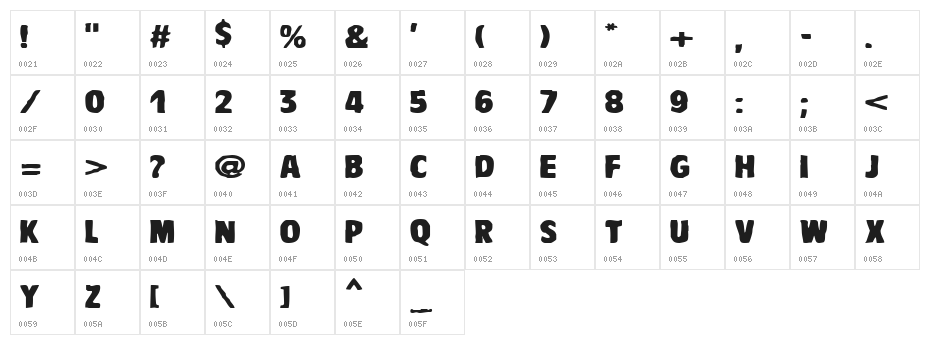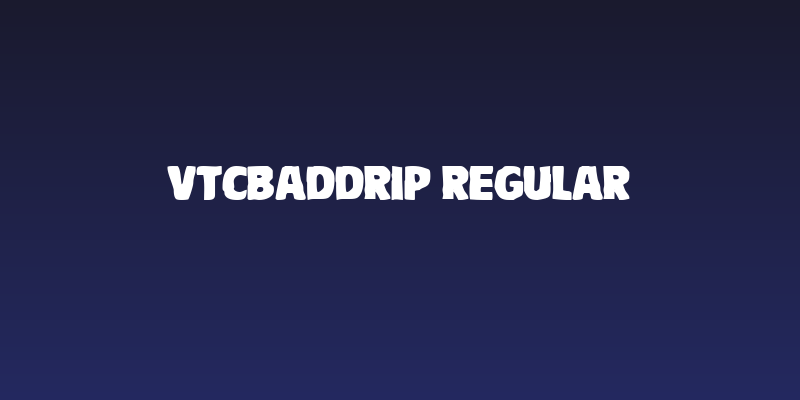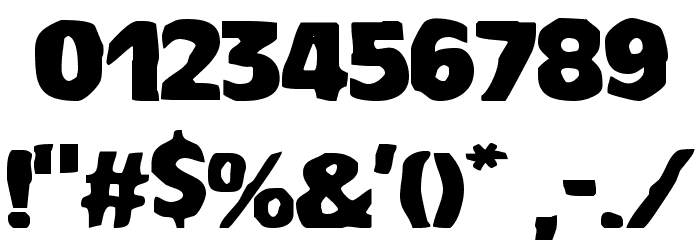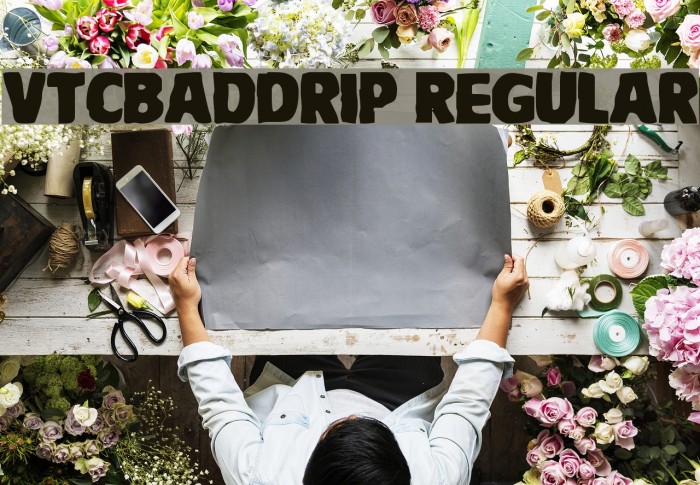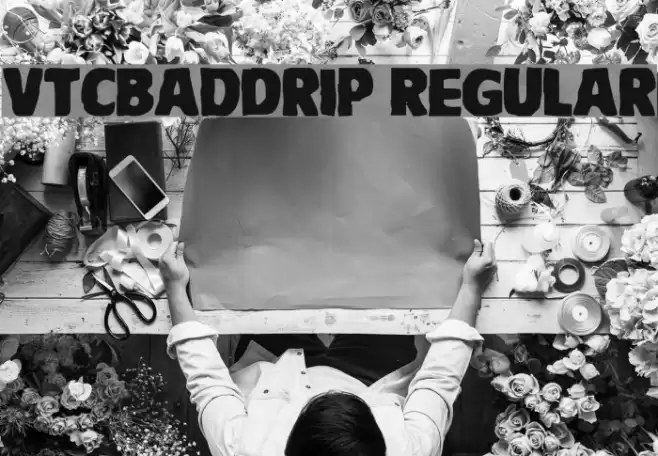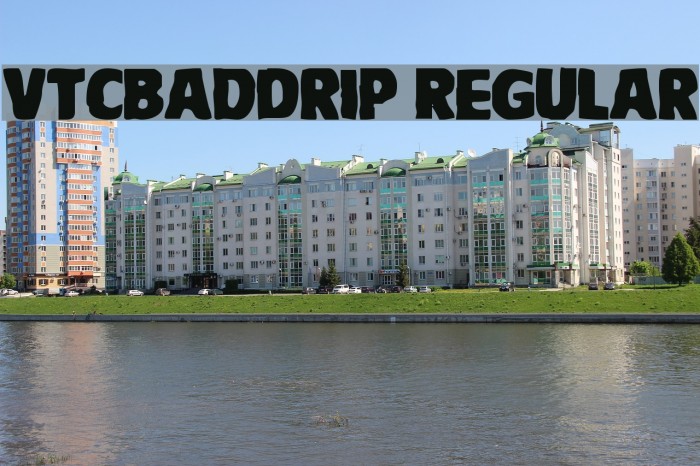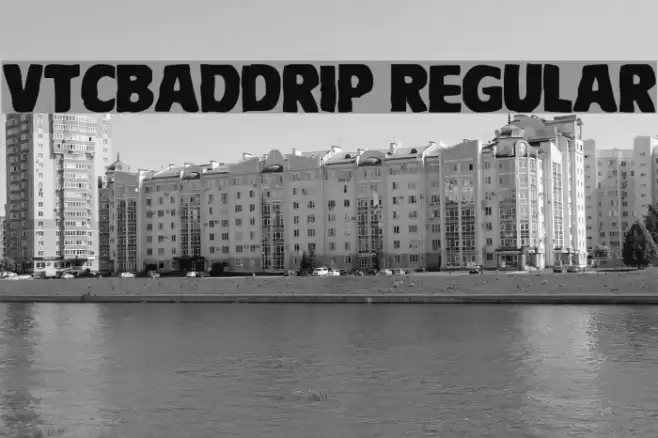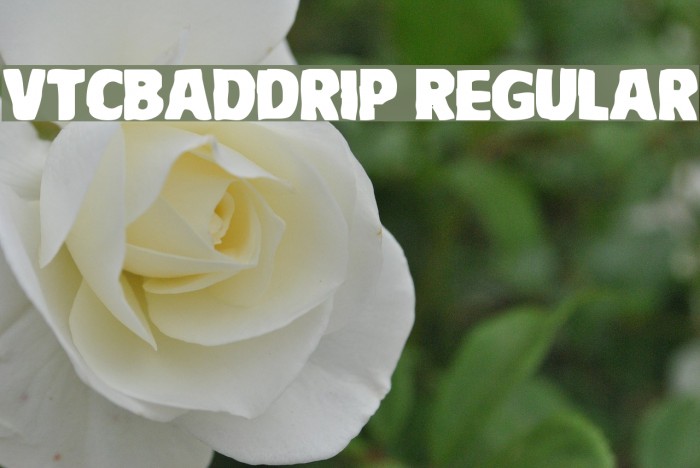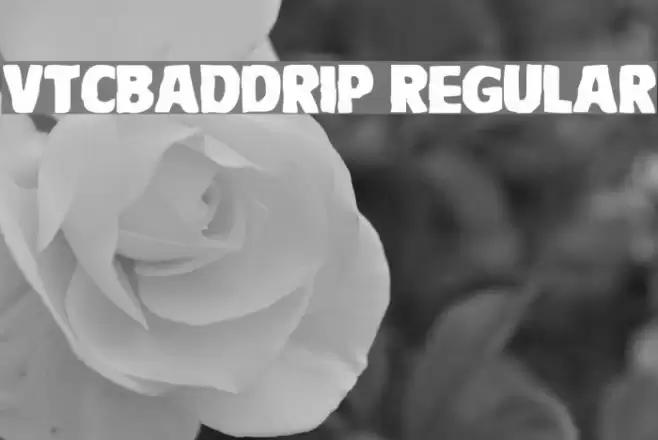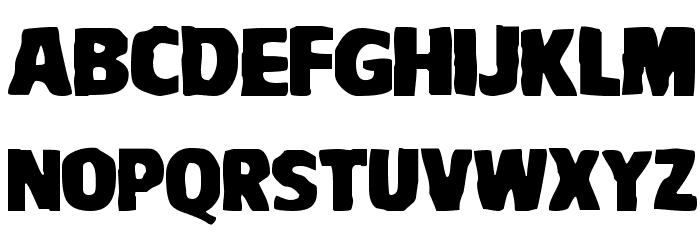
VTCBadDrip Regular Font
| Categorías | Capitals |
| Caso de uso | Headlines, Posters, Logos |
| Proyectos propuestos | Ideal for posters, album covers, children's books, and any project needing a lively, informal vibe. |